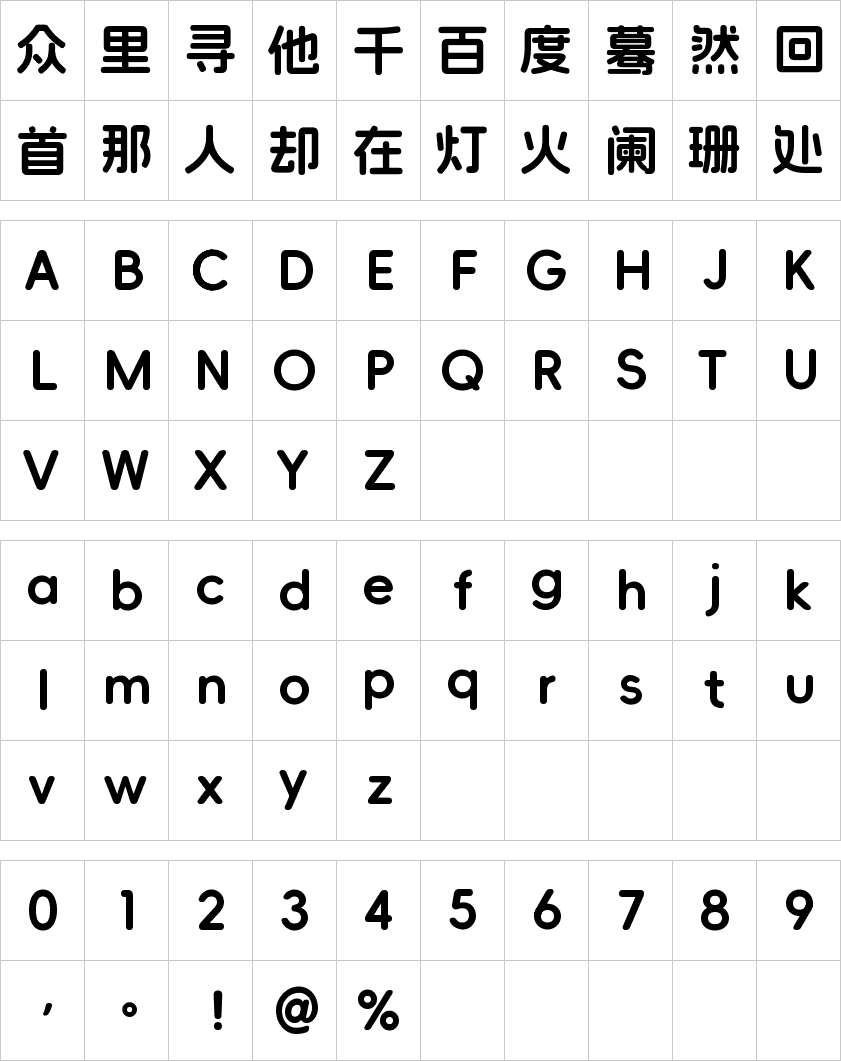
阿里妈妈方圆体
阿里妈妈方圆体为一款简体中文双轴可变字体,收纳的中文字符包括但不限于GB2312,共计6763个汉字;英文大小写共52个;常用标点符号共227个,总计7042个字符
设计说明:通过智能 AI 的方式在20天内完成的这款字,是目前国内外为数不多的中文双轴可变字体。方体坚实而硬朗,圆体润泽而柔美;方圆间的切换让方圆体极具适用性,也解放了创意表达的更多可能性。粗细的可变使得设计师具备无限微调的可能,让创意设计有了丰富表达。